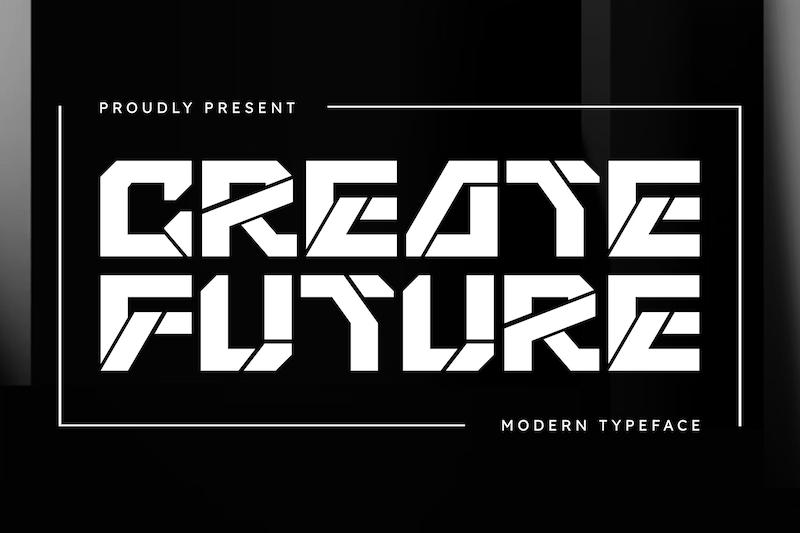
با فونت دیسپلی کریت فیوچر، لمس آینده در دستان شماست!
با قلم کریت فیوچر، پروژههای خود را به سطح دیگری ببرید! این فونت مدرن و آیندهنگر، بهترین انتخاب برای خلق طرحهایی است که جلب توجه میکنند.
مناسب برای: لوگوهای جذاب، برندینگ و تبلیغات، طراحی محصولات و لیبلها، مجله، دعوتنامه و...
پشتیبانی کامل (چندزبانه، حروف آلترنیت و لیگچر)
طبقهبندی: دکوراتیو